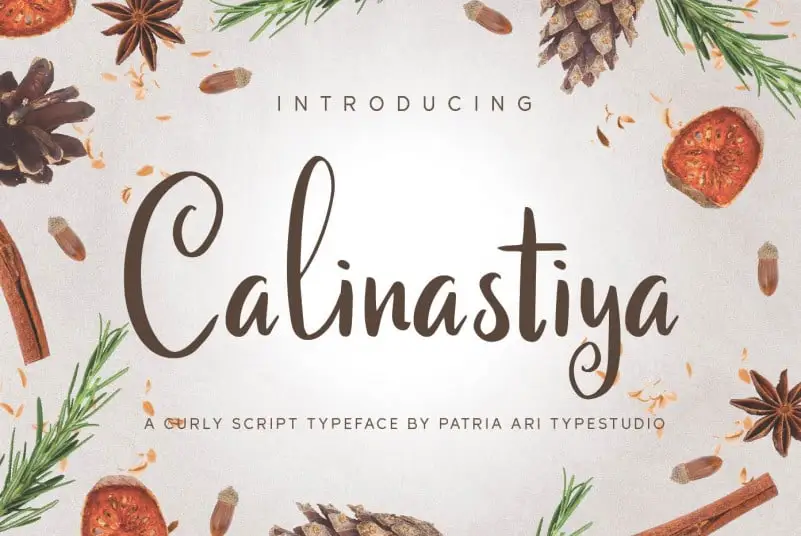
Calinastiya Script Font – Download Grátis
Calinastiya Script é uma elegante e curvilínea tipografia exibicional projetada para ser atraente e divertida simultaneamente. Especialmente indicada para aplicativos de marca, logomarcas, capas de livros, postagens nas redes sociais, anúncios, embalagens de produtos, design de produtos, etiquetas e qualquer projeto que você esteja trabalhando. Suas formas cíferas são tão bonitas quanto divertidas, tornando-a perfeita para dar um toque sofisticado e memorável a qualquer projeto de identidade visual. Calinastiya é a escolha ideal para quem busca uma fonte decorativa que combine elegância com graça descontraída.